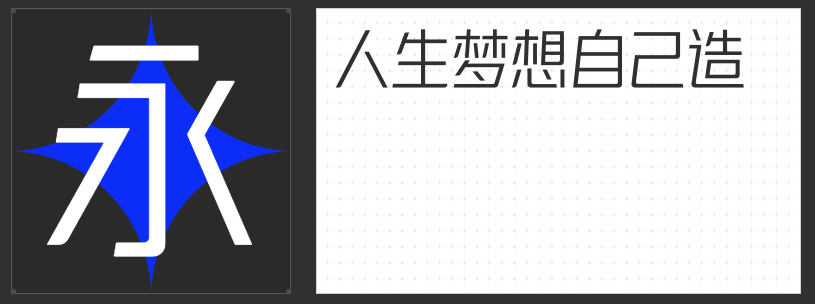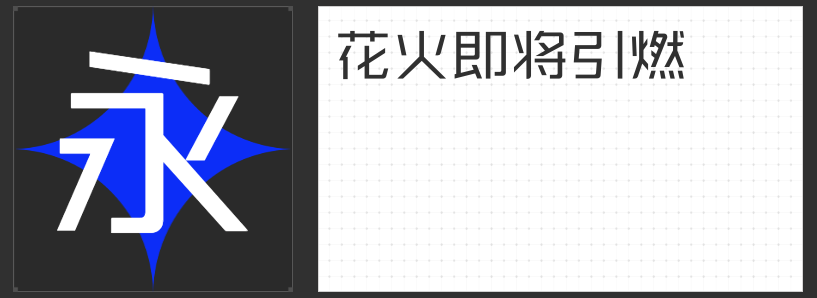
设计进阶之选:四款可变字体解锁动态视觉新维度
在数字化设计浪潮中,可变字体以其灵活的参数调节能力,成为突破传统排版局限的利器。通过调整字重、宽度、倾斜等维度,设计师可精准控制字体形态,实现从标题到正文的流畅过渡,或创造独具张力的视觉语言。以下四款可变字体,以独特的结构逻辑与动态美学,为设计注入多维可能性。
一、励字勇敢黑简 可变字体
作为无衬线字体的革新之作,励字勇敢黑简以粗壮笔划构建视觉锚点,横竖均匀的骨架确保远距离识别性,而撇捺的钝化处理则消解了锐利感,赋予文字沉稳气质。其可变特性支持字重从纤细到浑厚的无缝切换,既可压缩为紧凑标题,亦可拉伸为导视系统的核心符号,在标志设计中更可通过轴向变化强化品牌记忆点。
二、励字造梦简 可变字体
突破对称法则的励字造梦简,以左侧倾斜与右侧竖直的矛盾结构,模拟建筑透视的视觉张力。棱角分明的直线型笔画如同钢筋骨架,在可变参数驱动下可呈现从压缩到延展的形态变化,适配从狭长海报到宽屏数字界面的多元场景。其力量感与未来感并存的气质,尤为适合科技、建筑领域的视觉叙事。
三、励字可变志向黑简
融合圆体与黑体基因的励字志向黑简,通过外圆角处理软化传统黑体的机械感,在保持结构稳定的同时提升屏幕阅读舒适度。其可变设计聚焦于字面充实度与灰度均衡,设计师可微调字宽与笔画粗细,使文字在不同分辨率下均呈现饱满形态,成为移动端界面与长文本排版的理想选择。
四、字恋狂可变漫野
以手写肌理为底色的字恋狂漫野,通过直线组合与断笔处理打破常规手写体的随意感,布白空间的通透设计让文字呼吸感十足。其可变维度聚焦于字型大小错落与笔画灰度,设计师可模拟自然书写中的节奏变化,为版面注入人文温度,在文化类海报与艺术书籍设计中展现独特魅力。
可变字体的价值,在于将静态文字转化为可交互的视觉变量。这四款字体通过结构创新与参数开放,为设计师提供了从微观笔画到宏观版面的全维度控制权,助力创意突破媒介边界,构建更具生命力的视觉语言。